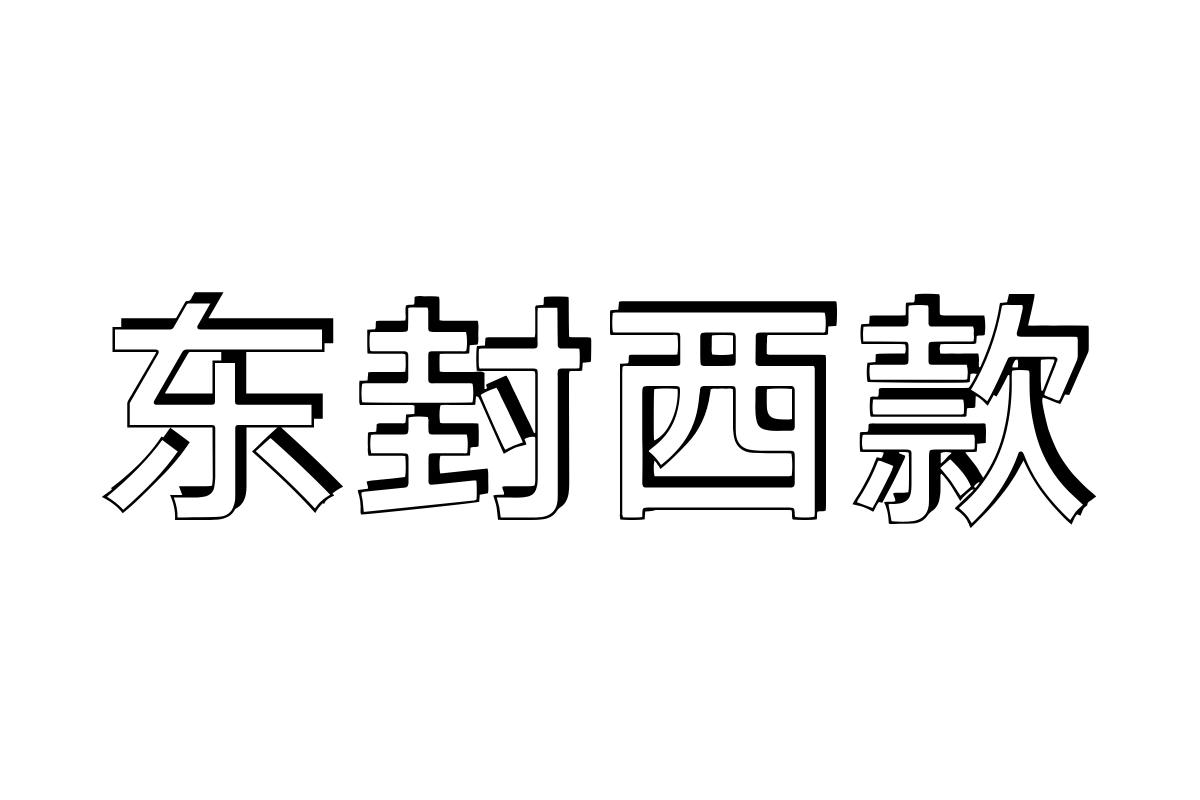
三极立体黑简体是一种新型的字体设计,它采用了现代的设计理念和创新的技术手段。这种字体具有独特的视觉效果,能够给人们带来一种全新的视觉体验。
首先,三极立体黑简体在字形结构上进行了大胆的创新。它的每个字符都采用了独特的形状和结构,使得整个字体看起来更加立体和动感。这种设计不仅增加了字体的美感,也使其在视觉上更具冲击力。
其次,三极立体黑简体在笔画的处理上也独具匠心。这种字体的笔画粗细不一,既有粗大的笔画也有细小的笔画,使得整个字体看起来既有力度又有细腻。这种处理方式使得字体更加生动和有趣,同时也能够更好地表达文字的含义。
此外,三极立体黑简体还注重字体的可读性。虽然它在字形上进行了创新,但在保持可读性方面却下足了功夫。这种字体的笔画清晰明了,即使是在远距离观看也能够轻松辨识。这使得三极立体黑简体在实际应用中具有很高的实用性。
总的来说,三极立体黑简体是一种非常独特的字体设计。它通过创新的字形结构和笔画处理,以及注重可读性的设计理念,为人们带来了一种全新的视觉体验。这种字体不仅美观大方,而且实用高效,值得大家尝试和欣赏。